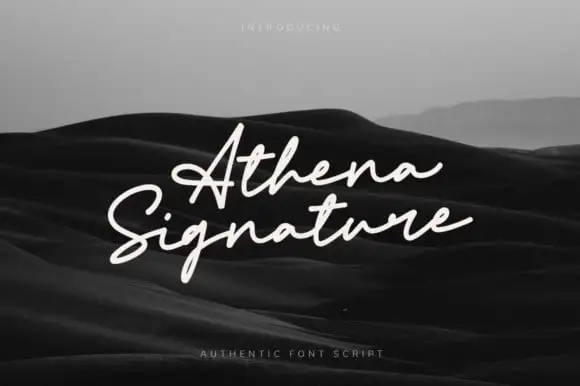
Athena Signature Script Font – Download Grátis
Athena Signature Script Font é uma nova fonte monoline que traz um estilo elegante com características chamativas e linhas suaves e lisas. Este tipo de fonte tem a beleza do gótico, mas também apresenta os detalhes fluidos de uma caligrafia sofisticada. Desenvolvida pelo agamous, esta fonte é perfeita para quem busca um ar de luxo em seus projetos digitais. Com linhas ideais que não são muito grossas nem finas, mantendo-se equilibradas e com variações sutis, Athena Signature Script Font será uma adição incrível à sua coleção de fontes. Seja para criar anúncios memoráveis ou design gráfico sofisticado, esta fonte é um elemento ideal que ajudará a destacar seus trabalhos. Não há dúvida de que Athena Signature Script Font irá transformar sua apresentação digital em algo singular e único.